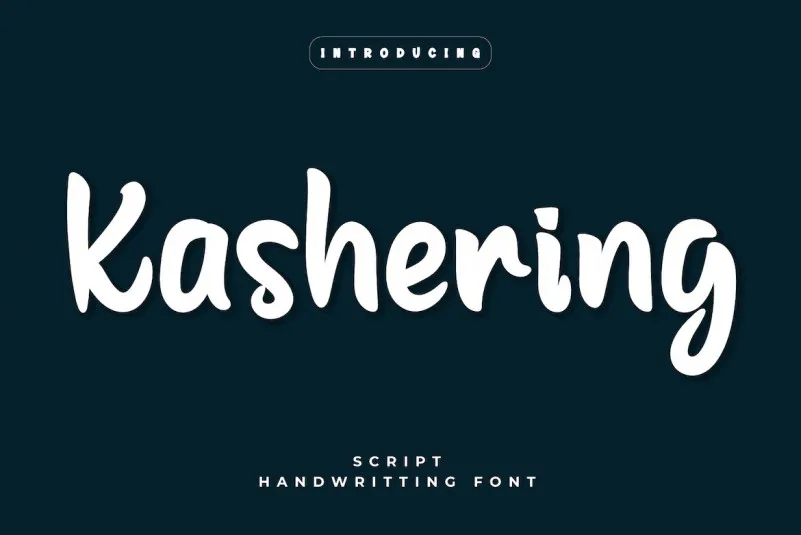
Kashering Font – Download Grátis
Esta é uma fonte projetada usando uma delicada mão do design, apresentando nuances belas e elegantes. Ideal para os projetos especiais onde deseja dar destaque à sua tipografia ou cabeçalhos. Esta font é um excelente complemento para qualquer projeto visual desejando trazer um toque agradável e sofisticado. Se você está procurando por uma fonte que possa destacar seu texto em projetos de design gráfico, esta pode ser sua escolha perfeita. Com um toque refinado e uma beleza inegável, a font ‘Kashering’ se destaca como uma opção elegante para os textos centrais ou capa de suas próximas criações digitais. Ela é ideal tanto para layouts digitais quanto para impressão, oferecendo um toque sofisticado que certamente fará seu design mais atraente e profissional.